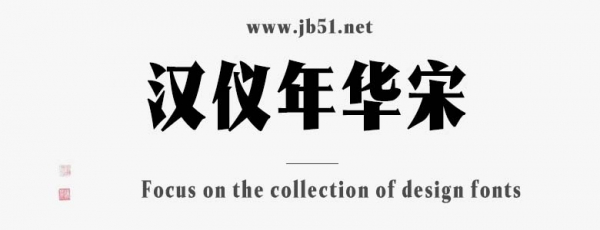
漢儀年華宋 U由漢儀字庫(kù)出品的藝術(shù)字體,字體筆觸適中,字形端正,具有很好的視覺(jué)感,適合應(yīng)用于藝術(shù)設(shè)計(jì)、平面宣傳設(shè)計(jì)、網(wǎng)頁(yè)設(shè)計(jì),書(shū)法字帖等領(lǐng)域。有需要的朋友快來(lái)本站下載使用吧。